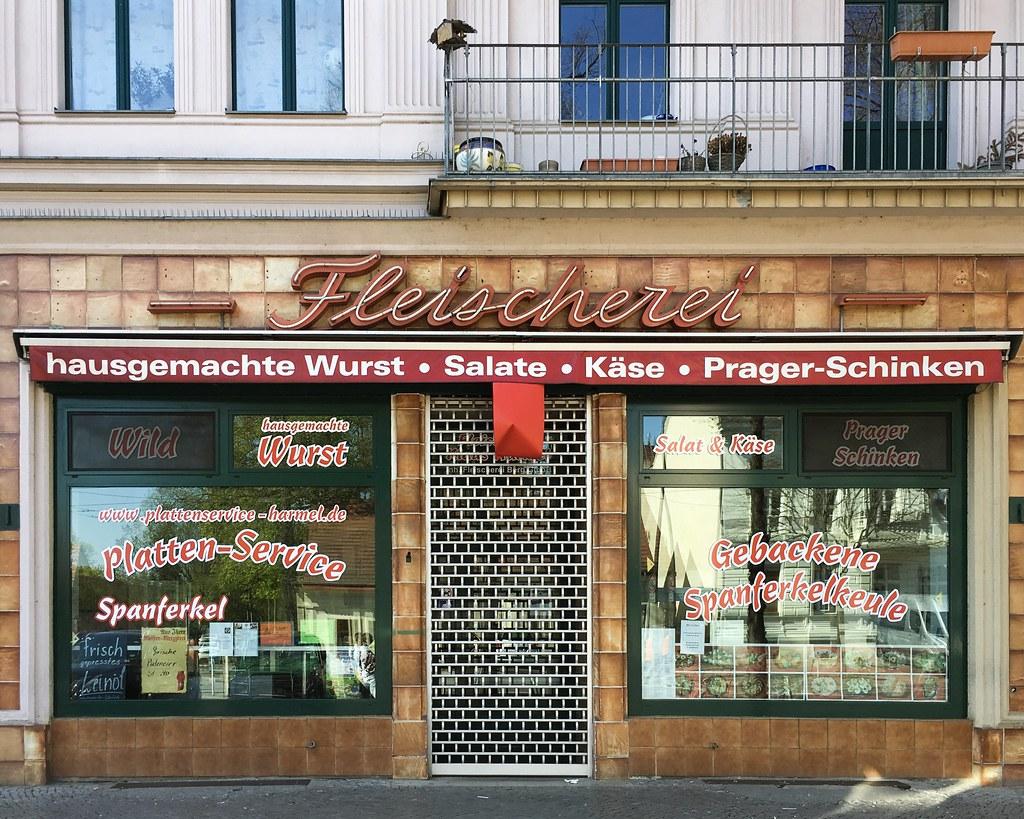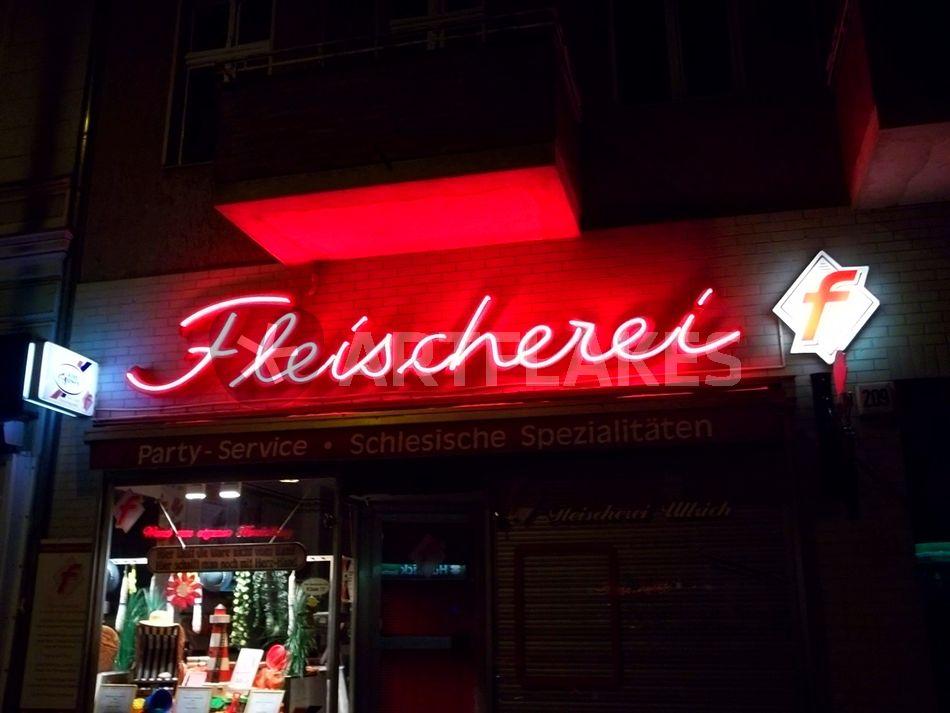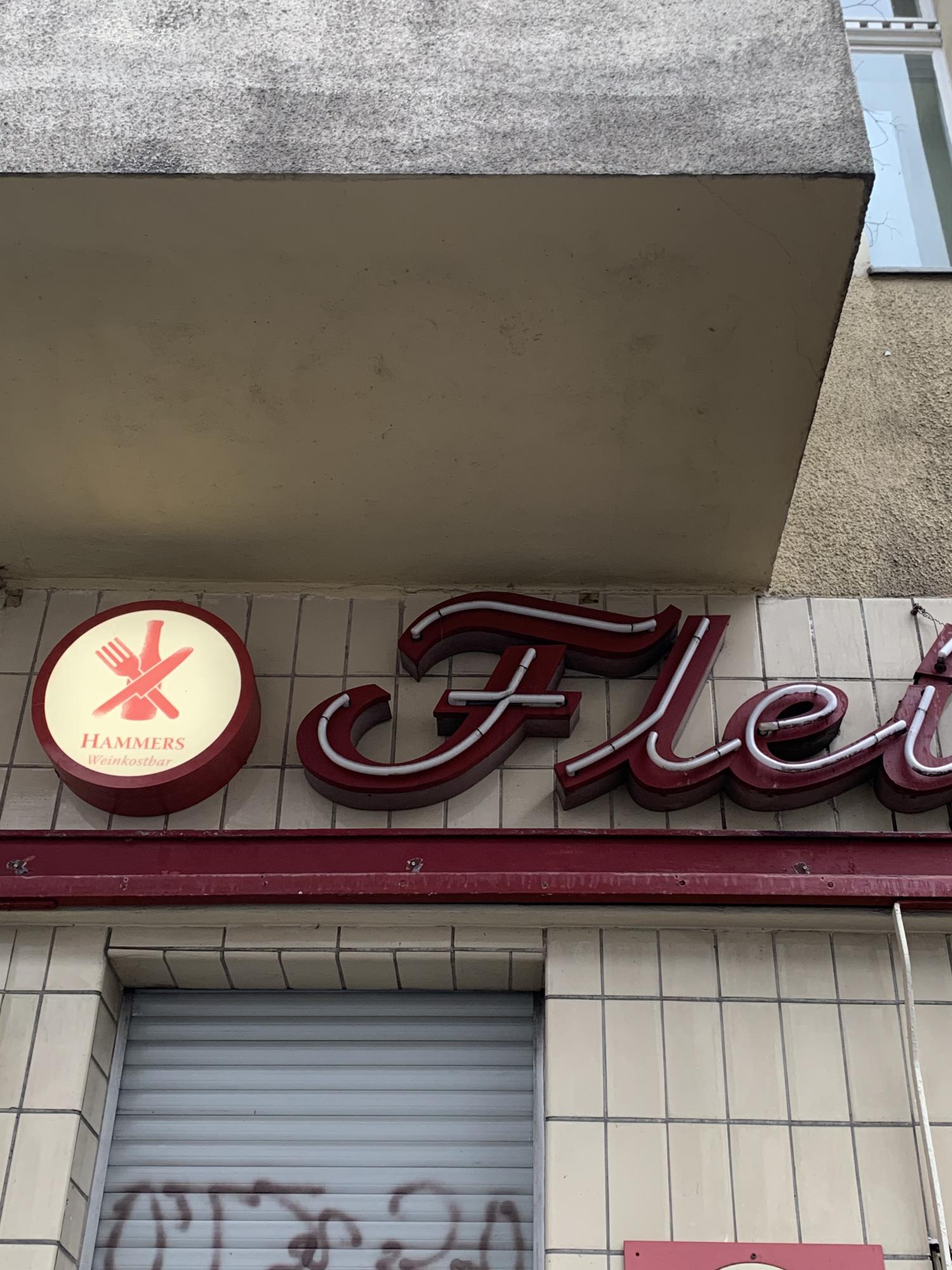
Fleischerei-Schriftzug – ich dachte das wäre ein Klassisker?
ich fahre fast täglich an diesem Schriftzug vorbei. Ich glaube sogar das so ein »F« im Buchstabenmuseum steht. Aber ich finde keine Entsprechung um auf diesen Font zu schließen. Ist es gar kein Font?  Ich dachte es sei so ein klassischer Schriftzug, den man an vielen alten Fleischereien findet.
Dem ist aber nicht so.
Jemand ne Idee?
Nein, das ist gar kein Font, sonder der wurde Mund geblasen, bzw die Anschluss-Kästen unter der Neonschrift vom Leuchtreklame-Hersteller von Hand gezeichnet. Schriften zeichnen gehörte in der Zeit solcher Neonreklame noch zur Berufsausbildung, genau wie zu der von Malern, Lackierern, hier speziell auch Schildermalern, Steinmetzen  und natürlich auch Grafikern, die sich auf "Gebrauchsgrafik" spezialisiert hatten.
Darum ist auch jede Neon-Schrift praktisch ein individuelles Einzelstück, bzw muss bei Nachbestellung der 1:1-Zeichnung  nachgebogen werden.
Ach so, auch wenn dies hier jetzt kein Font ist, habe ich sehr wohl etwas entsprechendes gebaut:
Mir kommt es auch vertraut vor. Es gibt halt auch Trends und Moden ...
Ganz bestimmt. Diese Auszüge aus "Die Schriften des Malers" von 1956 hauen da alle in die gleiche Kerbe.